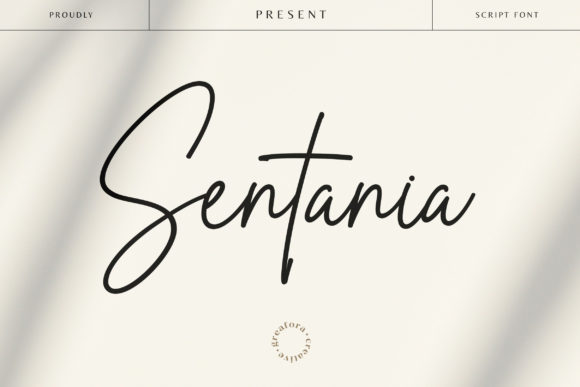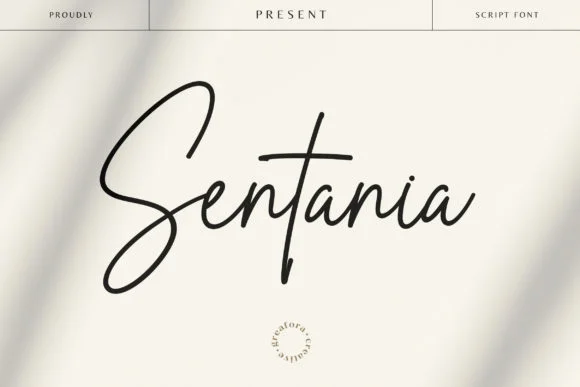
Название: Sentania Font (2021)
Sentania - это милый и простой рукописный шрифт, который можно использовать для всех цитат на меловой доске или учебных материалов!
Его аутентичный вид придаст вашим проектам индивидуальность и реалистичность.
Название: Sentania Font (2021)
Sentania - это милый и простой рукописный шрифт, который можно использовать для всех цитат на меловой доске или учебных материалов!
Его аутентичный вид придаст вашим проектам индивидуальность и реалистичность.